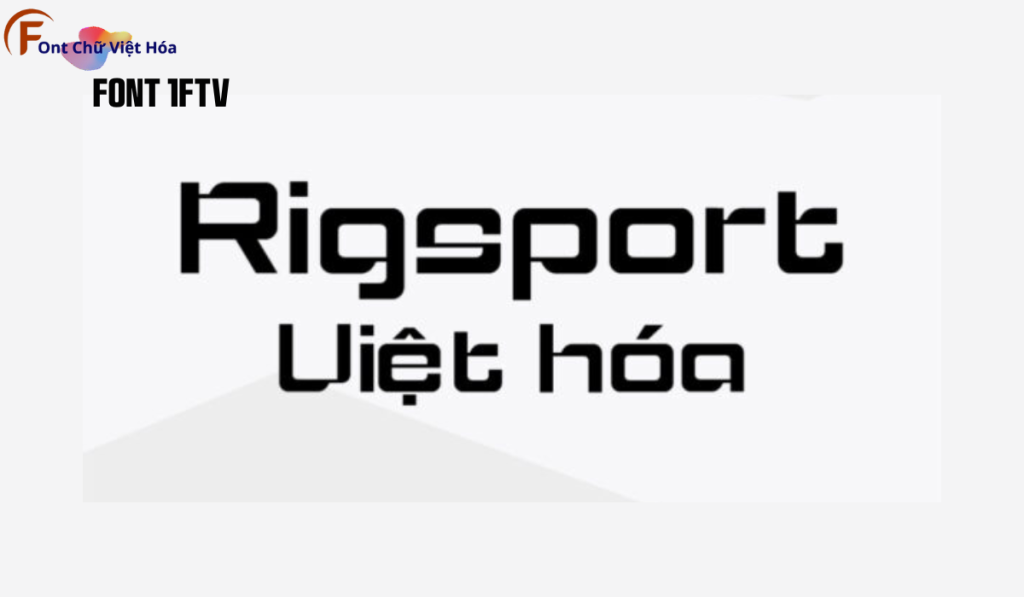
Font 1FTV Rigsport
Kiểu chữ: Sans-serif
Font 1FTV Rigsport là một font chữ độc đáo, thuộc bộ 1FTV, nổi bật với phong cách sans-serif hiện đại và các đường nét mạnh mẽ, thể thao. Thiết kế của 1FTV Rigsport tập trung vào sự năng động và dễ đọc, đặc biệt phù hợp cho các thiết kế đòi hỏi tính thẩm mỹ cao như poster, logo, và tiêu đề. Với tỷ lệ chữ cân đối và các đường nét đậm, font này tạo ra ấn tượng thị giác mạnh mẽ và giúp tối ưu hóa không gian trong thiết kế. Font này cũng đã được Việt hóa, mang đến sự linh hoạt và tiện dụng cho các dự án thiết kế bằng tiếng Việt